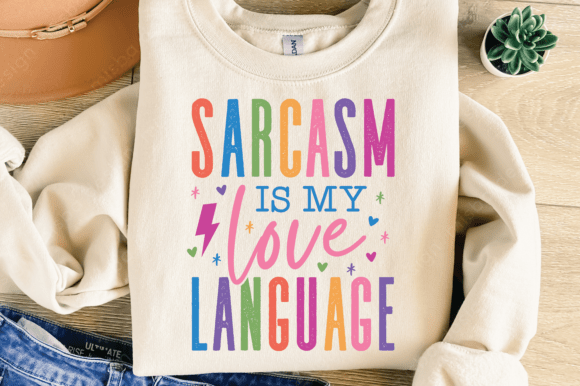
Selina Daniel Duo Font
Die richtigen Designelemente zu finden, kann eine Herausforderung sein, aber Selina Daniel Duo Font bietet eine außergewöhnliche Sammlung, die Ihre Arbeit sofort aufwertet.
Egal, ob Sie POD-Produkte (Print on Demand), Hochzeitseinladungen oder Social-Media-Grafiken erstellen, Selina Daniel Duo Font ist die ideale Wahl.